「Y2K」にぴったりの日本語フリーフォント
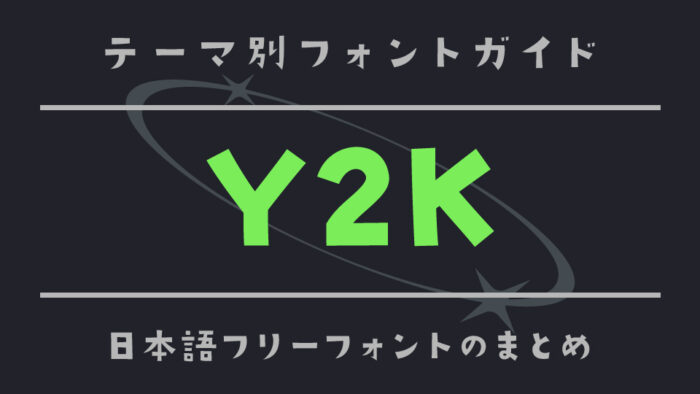
今回は、2000年代初頭のサイバーでポップな空気感をまとった「Y2K(「Year 2000)」スタイルにぴったりな日本語フリーフォントをご紹介します。
Y2Kといえば、メタリックな光沢、未来感あふれる曲線、テクノポップなな雰囲気をデザインです。そんな懐かしくも新しい“近未来レトロ”の世界観が「Y2K」の特徴です。ファッションや音楽、映像などで再び注目を集めているこのY2Kスタイルは、文字選びひとつで一気に雰囲気が完成しますよね。
今回は、90年代後半〜2000年代初頭のテンションを感じさせる日本語フリーフォントを厳選しました。デジタル感あふれるロゴやポスター、ZINE、MVのタイポグラフィにもおすすめです。
懐かしいのに新しい。Y2Kな雰囲気のある日本語フリーフォント集
レトロ×フューチャーなもつ「Y2K」の雰囲気にぴったりなフォントをご紹介します。
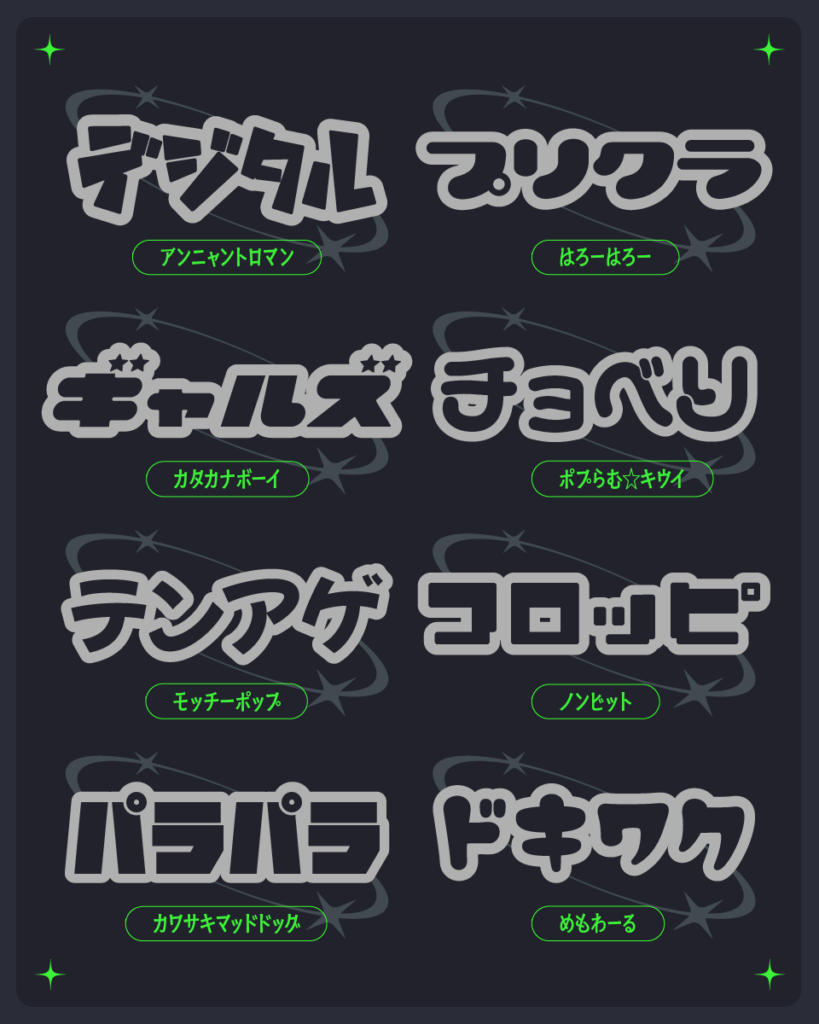
ノンビット
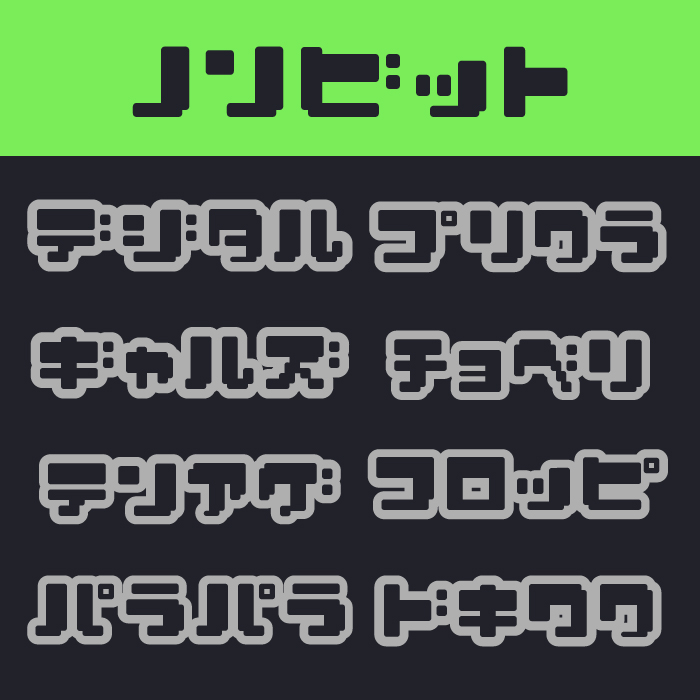
ノンビットフォントは、ゲームボーイやレトロな電子機器を連想させるピクセル風デザインが特徴フォントです。直線的で角ばった形状ながらも親しみやすさがあり、90年代のポップカルチャーを感じさせるフォントです。
モッチーポップ
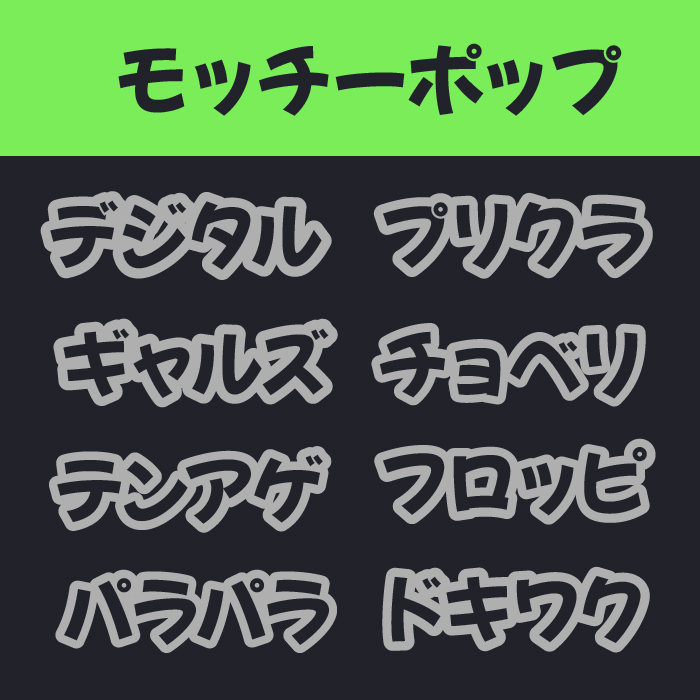
モッチーポップフォントは、手描きのような柔らかい輪郭とリズムのある傾きが魅力のポップ系フォントです。懐かしさと楽しさがあり、ガーリーで賑やかなY2K感を表現できます。
ポプらむ☆キウイ
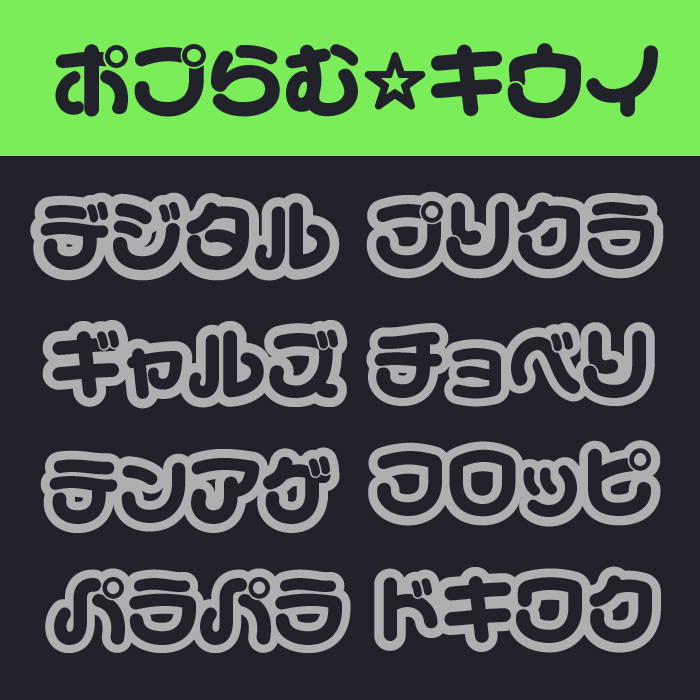
ポプらむ☆キウイフォントは、丸みを帯びた形状に加え、星マークなどの遊び心ある装飾がちりばめられています。アイドル文化やプリクラブームと相性が良く、キラキラした雰囲気が漂うフォントです。
カタカナボーイ
カタカナボーイフォントは、斜めに跳ねたような文字の傾きと星付き装飾が特徴的なフォントです。スピード感と勢いを感じさせ、Y2K時代の「やんちゃポップ」な空気感をそのまま映し出したようなフォントです。
はろーはろー
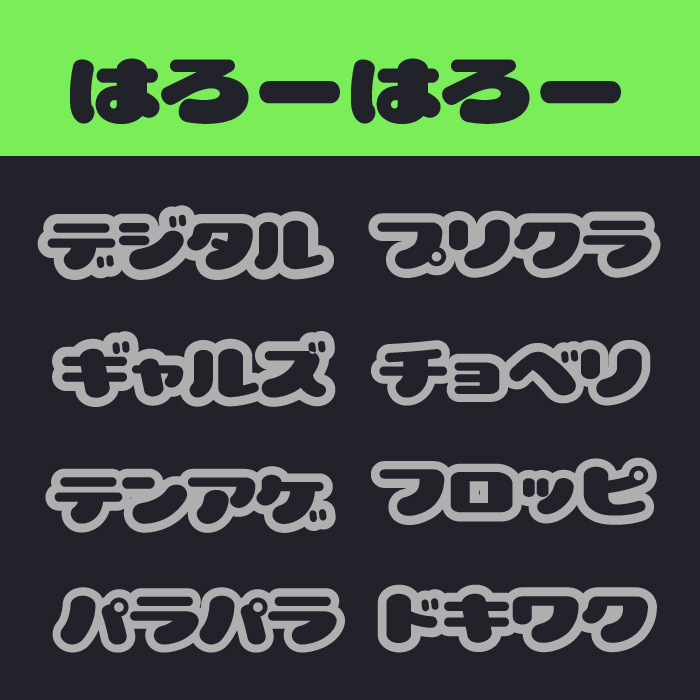
はろーはろーフォントは、柔らかくぷっくりとした輪郭により、明るくポップな印象を与えるフォントです。親しみやすく軽やかな文字の形は、デジタル黎明期のグッズやパッケージにマッチしそうです。
ヤデワのジ
ヤデワのジフォントは、分厚いエッジと直線的なシルエットで、力強さとインパクトを演出するフォントです。Y2K時代のストリート感とビビッドな存在感が漂い、タイトルロゴにも最適です。
めもわーる
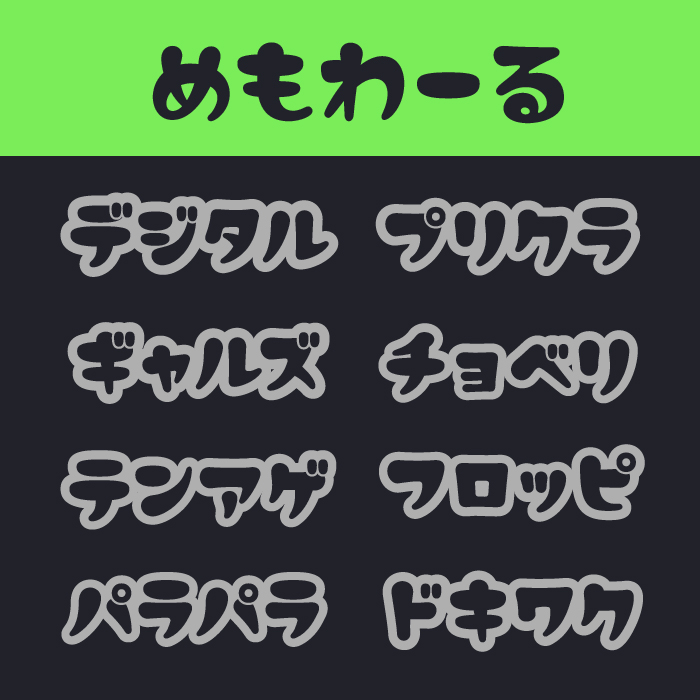
めもわーるフォントは、曲線的でやさしいタッチがありつつ、少しクセのある形が印象的なフォントです。どこか懐かしく、00年代の少女文化や手書きPOPとマッチするフォントです。
アンニャントロマン
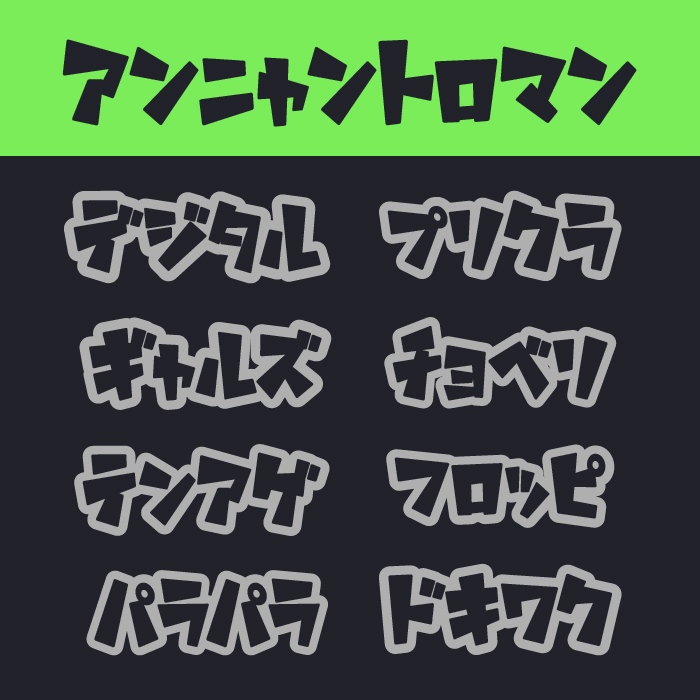
アンニャントロマンフォントは、ゆがみと跳ねが混在するラフな筆致が特徴です。ちょっとした違和感や反骨感があり、Y2Kらしい混沌とした魅力を持ったユニークなフォントです。
どんぐりデュエル
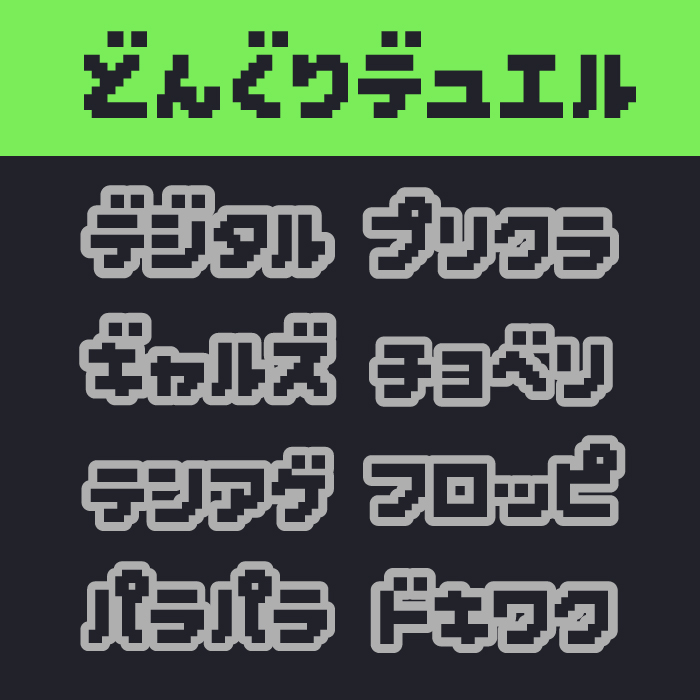
どんぐりデュエルフォントは、ドット絵のようなブロック感と絶妙なレトロさが光るフォントです。かつてのテレビゲームやB級ホラータイトル風のテイストを再現できる、個性派のフォントです。
カワサキマッドドック
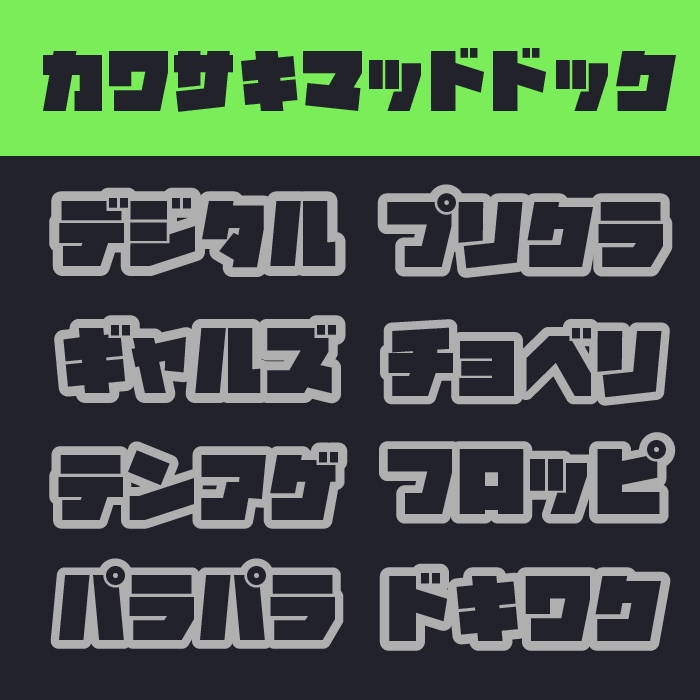
カワサキマッドドックフォントは、極太のゴシック体に近い迫力ある形が特徴で、90年代アーケードゲームやステッカー文化を思わせる力強さがあります。ワイルドなY2K感にぴったりです。
Cherry Bomb
Cherry Bombフォントは、ぷっくり丸くて弾けそうな文字のシルエットが印象的なY2K感あふれるフォントです。プリクラ文化やギャル文字のような空気感があり、90年代~2000年代のカルチャーが好きな人に刺さるテイストのデザインフォントです。